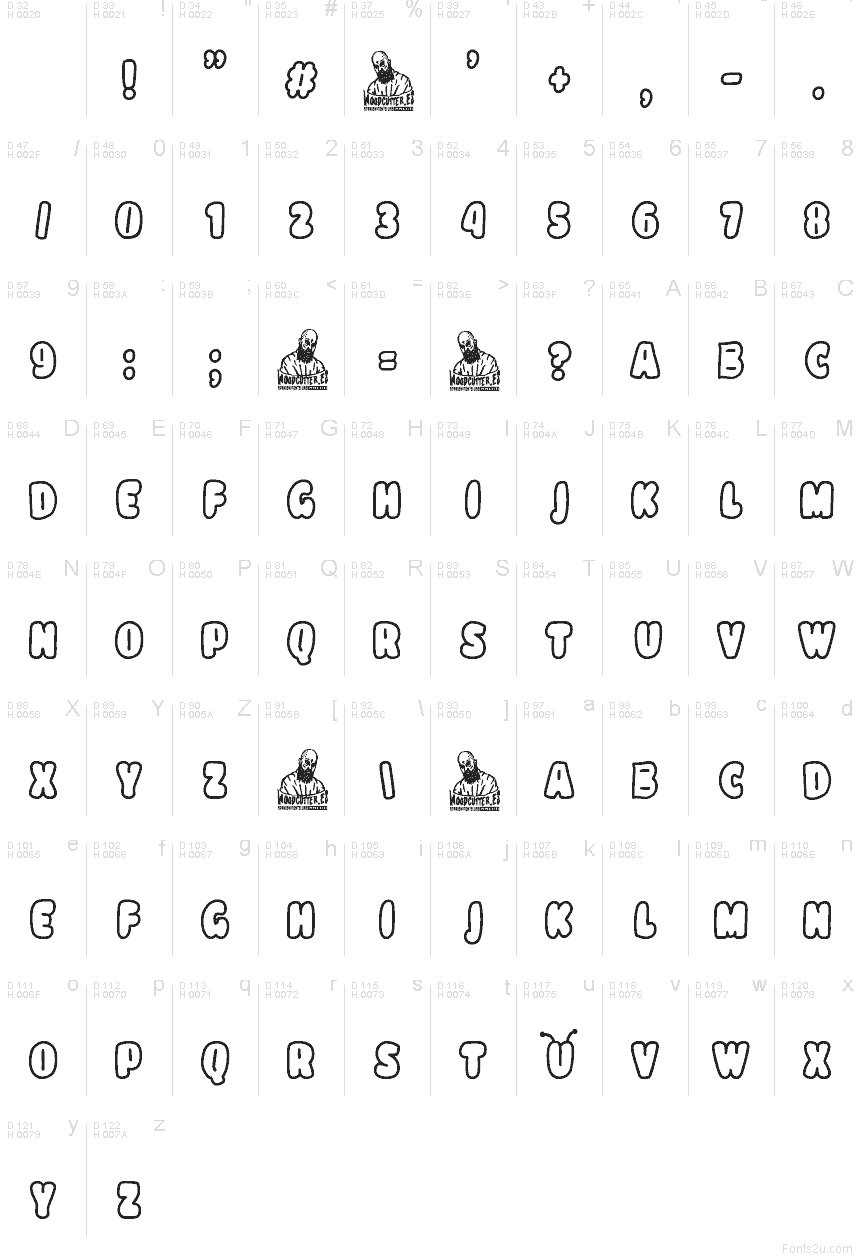
Chapulines
Chapulines od Woodcutter Manero je bezplatné kreslené display písmo s robustnými, zaoblenými znakmi a hravým nádychom pripomínajúcim hmyz. Abeceda pôsobí mäkko a živivo, s výrazným čiernym obrysom a bacuľatými tvarmi. Tento prvok inšpirovaný hmyzom dodáva sade energiu drzej maskotky, ktorá ďaleko presahuje bežný komiksový vzhľad.
Tento bezplatný font sa skvele hodí na obálky detských kníh, obaly dobrôt, párty plagáty, nálepky a titulky, ktoré potrebujú ľahký, animovaný tón. Funguje dobre aj pre krátke nadpisy a monogramy, pretože písmená sú dostatočne široké, jednoduché a charakterne výrazné, aby obstáli samé o sebe.